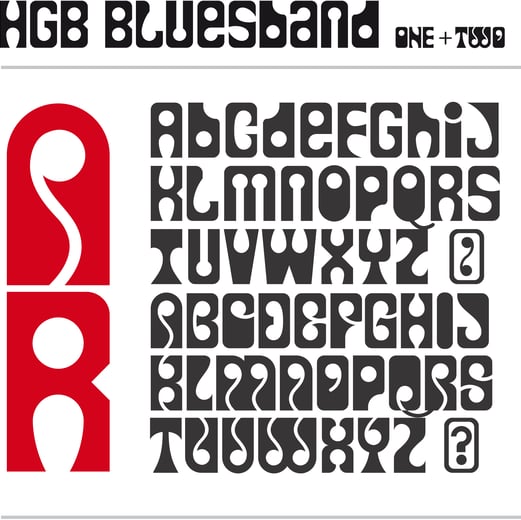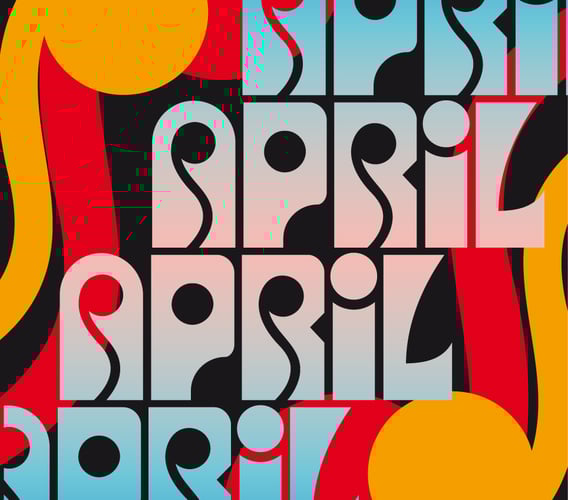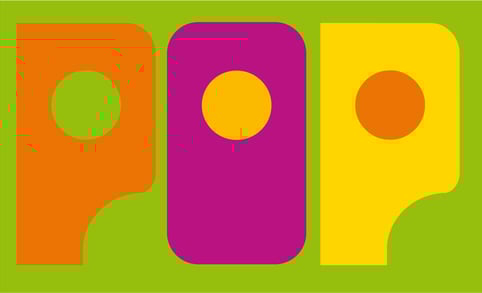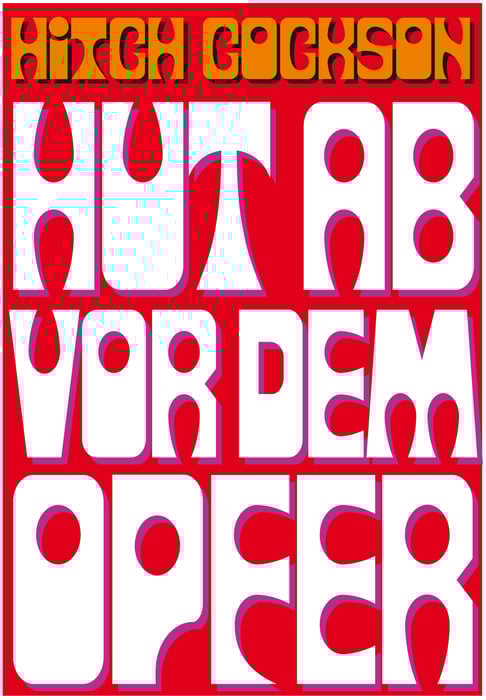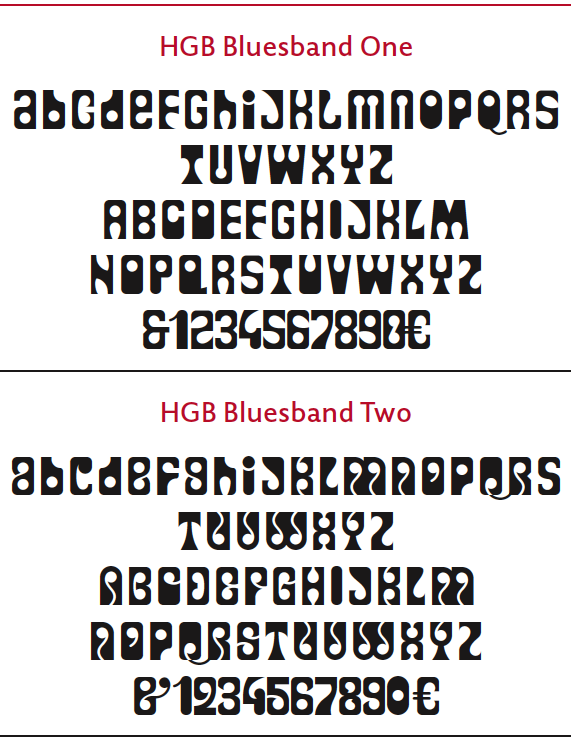
HGB Bluesband
Als Filmrequisite für einen Super-8-Spaßfilm entstand 1967 völlig unbedarft ein Buchtitel »Hut ab vor dem Opfer« in poppigen Lettern. Den Buchtitel hatte ich mit Filzstift und Plakatfarben gemalt, ohne viel nachzudenken. Dass dies ein erster ungelenker Schriftentwurf war, fiel mir erst gute 50 Jahre später auf. Die ganze Flower- Power-68er-Hippie-Atmosphäre war hier unbewusst eingefangen. Ab 2019 habe ich die wenigen Buchstaben ergänzt und mit Varianten versehen, die mir damals nicht eingefallen wären.